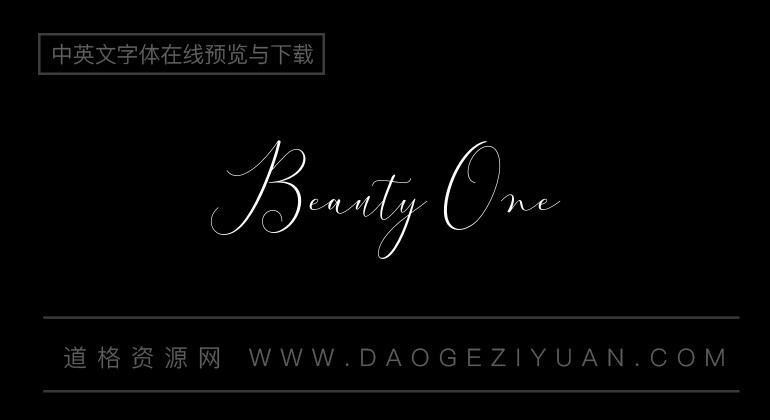
Beauty One 是一款英文字体,由英国设计师 David Kerkhoff 创作,于2009年发行。Beauty One 字体采用均衡的线条,更加优雅,更加精致,拥有超过400个字符,包括大小写字母、数字、标点符号、希腊字母等。Beauty One 字体的特点是简洁大方,拥有细腻的线条,能够给文字带来更加优雅的美感,适合用于商业广告、报刊杂志、海报、书籍、电子商务等领域的文字排版。内容介绍
Beauty One是一款非常不错的手写艺术字体,具有很好的视觉感,适合于文化类的宣传设计、商业类品牌的广告和产品包装设计以及个性化文字排版等较多场景。